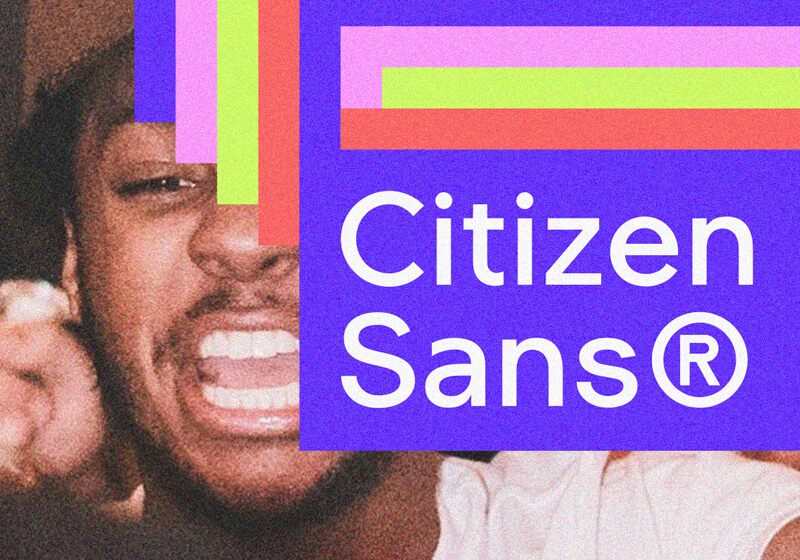
Citizen Sans Public je bezplatné bezpatkové písmo se zaoblenými křivkami, otevřenými tvary a jednoduchým geometrickým rytmem, který dává písmenům klidný a přímočarý vzhled. Tvary zůstávají čisté a rovnoměrné, s měkkou křivkou u písmene C a kompaktní, vzpřímenou strukturou, díky níž celek působí uspořádaně, aniž by byl strnulý.
Citizen Sans Public se dobře hodí pro webové štítky, rozhraní aplikací, značení, krátké popisky a branding, který vyžaduje srozumitelný a spolehlivý hlas. Toto bezplatné písmo se také hodí pro plakáty, navigační systémy a redakční nadpisy, protože jeho jasné tvary drží pohromadě v krátkých a funkčních textech.
Jednoduché, moderní a univerzální bezpatkové písmo.
Citizen Sans
Public
Luke Ferrand